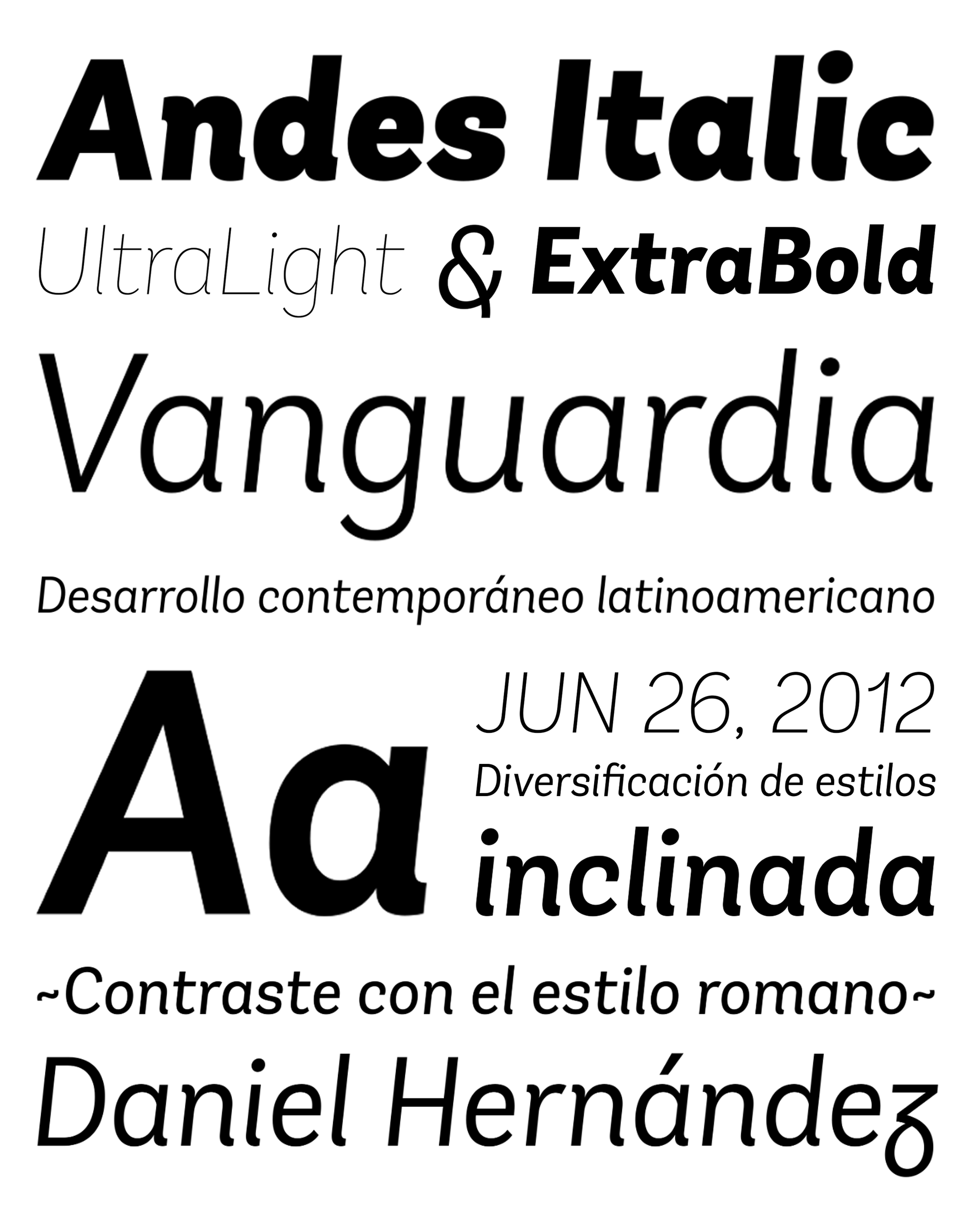
| Año | 2012 |
| Créditos | Daniel Hernández |
| Descripción | Andes, diseñado por Daniel Hernández, es un tipo de letra para pantalla de características neohumanistas. Sus diferentes terminales, entre otros elementos, le dan un aspecto de tipografía mixta. Andes es un tipo de letra con 10 Vertical pesas, 10 Cursiva & Versión resumidaLos caracteres de este tipo de letra van de Ultra Light a Black, cada uno con la misma altura x. Este tipo de letra contiene glifos cursivos adicionales (a, y, z, g) que ayudan a enfatizar el texto o las palabras. Andes se basa en el diseño de Merced y ambos comparten varias características. Este tipo es muy adecuado para su uso en comercios, revistas, logotipos, libros, etc. |